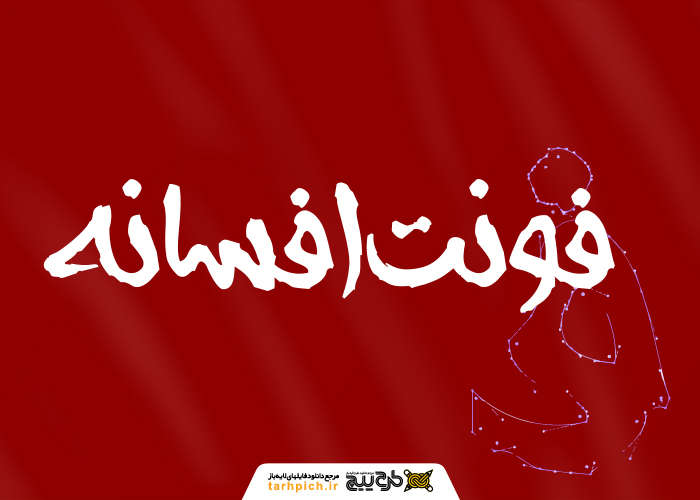
فونت فارسی افسانه یکی از پر کاربرد ترین فونت های فارسی است که توسط آقای حسین تقی زاده در سال 1395طراحی شده است .
در این فونت از فرمت TTFاستفاده شده است.طراحان وب سایت و گرافیست های خلاق می توانند از این فرمت زیبا در طراحی خود استفاده کنند.همچنین فونت افسانه نوعی فونت تایپوگرافی است.فونت افسانه از سری فونت های آزاد است و جزء دسته بندی فونت فارسی به حساب می آید.این فونت جذاب حالت رسمی داشته که شما می توانید در کارهایی مثل طراحی بنر های رسمی و آموزشی از آن استفاده کنید.اگر به دنبال فونت رایگان هستید روی لینک رنگی کلیک کنید.